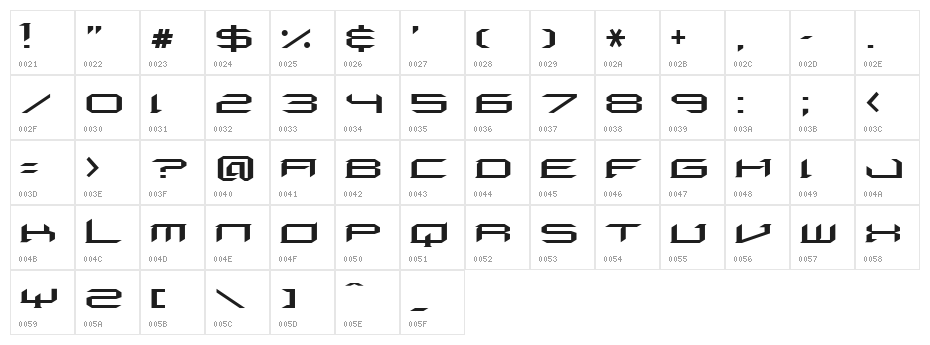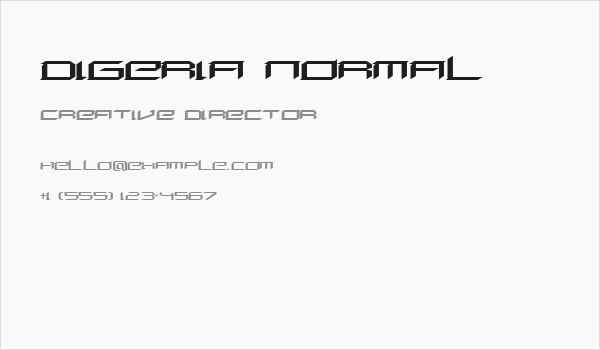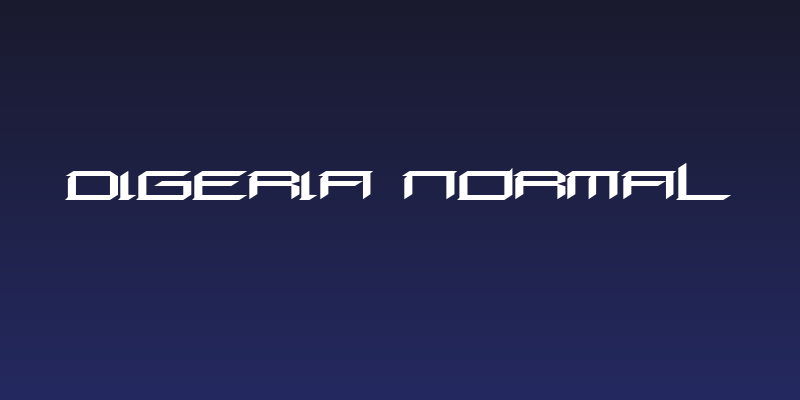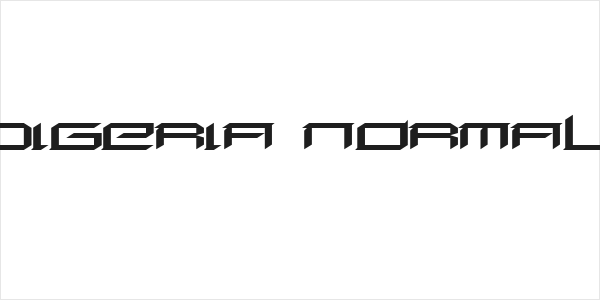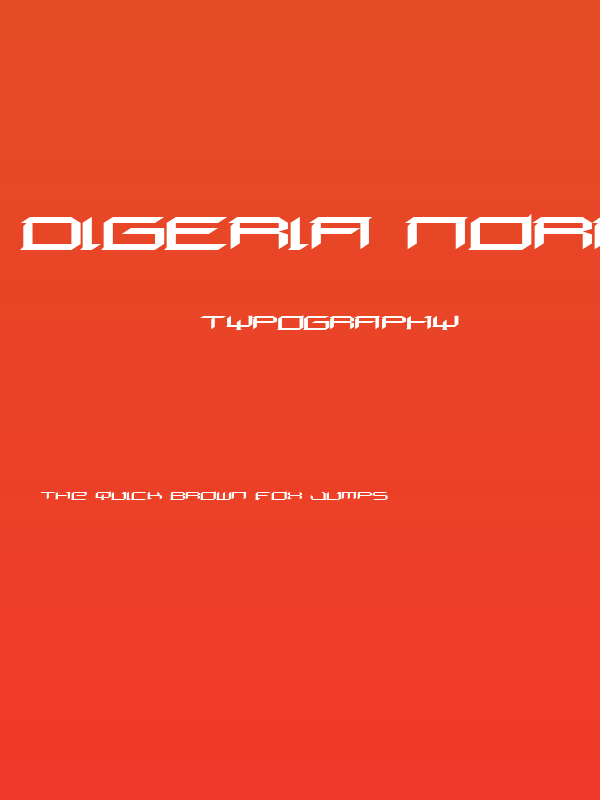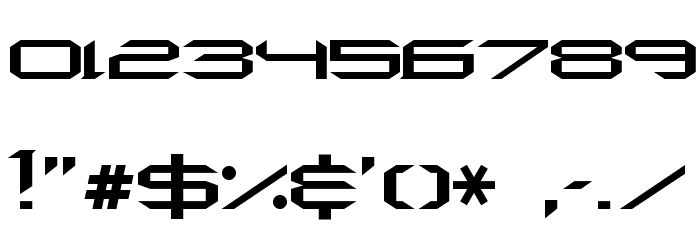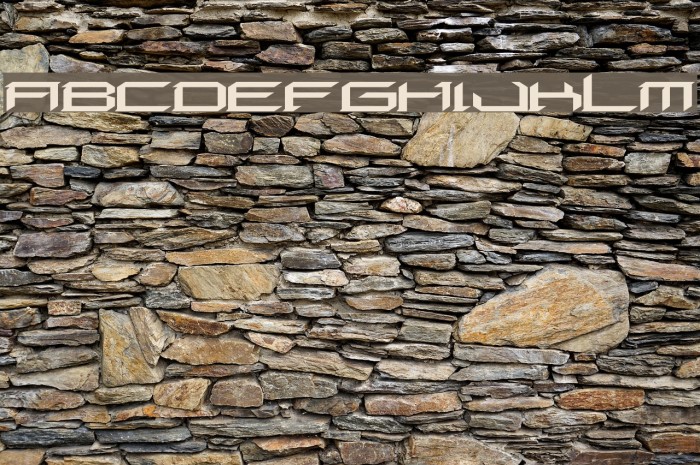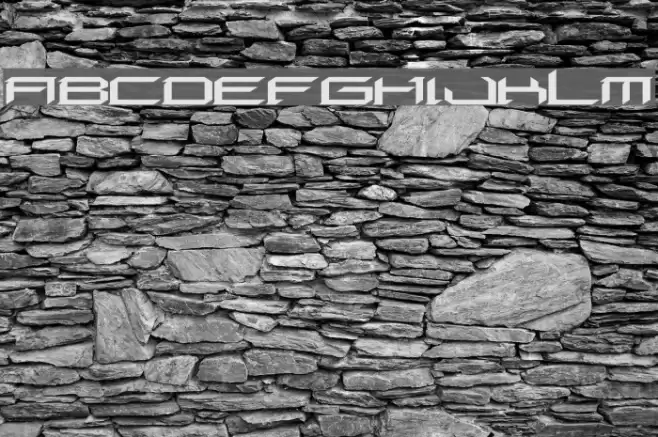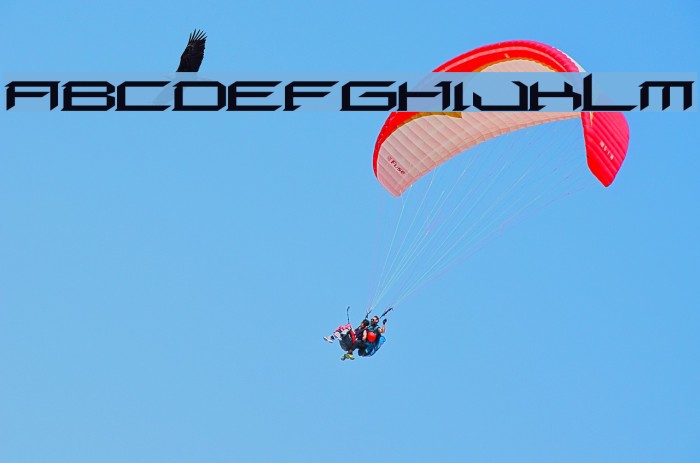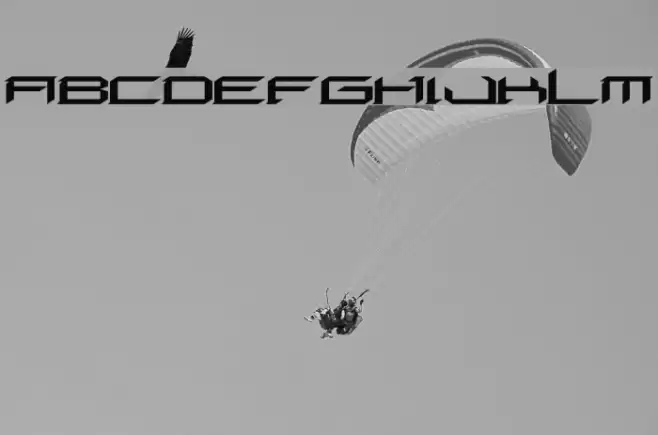
Digeria Normal Font
| Anwendungsfall | Logos, Headlines, Posters |
| Vorgeschlagene Projekte | Ideal for technology branding, sci-fi movie posters, video game titles, and modern digital interfaces. |